为您推荐以下字体侵权案例:
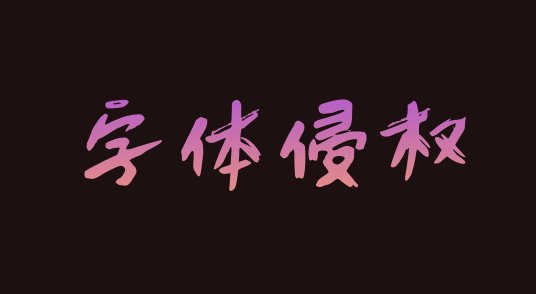
字体侵权案例1、关于字体侵权的案例,近期发生的。关注字体的应该都清楚,(电影《九层妖塔》字体侵权案有了最终的判决,7个字14万?)
据南都此前报道,向佳红起诉时称,电影《九层妖塔》中有七个字采用了其创作的字体,分别是鬼、族、史、华、夏、日、报。而《鬼族史》与《华夏日报》道具在影片中占有主导分量,是剧情的重要组成部分。“但我并未授权任何单位和个人使用‘向佳红书法字体’,更未允许任何单位和个人将字体用于商业营利和传播。”向佳红称,其在此套字体的属性中明确注明,该字体仅限于学习与交流使用,对个人用户免费,但商业用途须需经其本人授权。2013年12月,向佳红向广东省版权局申请作品名称为“向佳红毛笔行书字体”的作品著作权登记。
一审中,被告方辩称,涉案字体不是向佳红创作的,其对此不享有著作权;涉案单字仅出现在电影道具中,目的仅为说明道具名称,为汉字基本使用方法,在于传递其所承载的中文语言含义,而非主要展示其作为美术作品的艺术价值。此外,该使用方法使涉案单字具有了新的意义及功能,未影响其作为美术作品的正常使用,属合理使用。
一审法院经审理认为,向佳红主张权利的7个单字在断笔方式、布局结构、笔画粗细等方面均体现出了独特的美感。呈现出了不同于传统行书及其他常见字体的独创性表达,融入了书写者独特的智力判断和选择,属于我国著作权法中规定的美术作品。最后,四被告被判共同赔偿向佳红14万元。
一审判决后,梦想者电影(北京)有限公司、中国电影股份有限公司继续提起上诉,认为《九层妖塔》中对向佳红主张权利的7个单字的使用未违背其创造意图,其使用属于对涉案做转化性使用。同时,电影中对涉案作品使用仅作为道具的组成部分,在影片中短暂出现,如果署名会破坏电影画面的完整性。
二审法院经审理认为,电影拍摄过程中对涉案7个单字的使用属于复制行为,该行为未得到权利人的许可,即侵犯了著作权中的复制权,也不属于合理使用。最终,驳回上诉,维持原判。
字体侵权案例2、方正起诉暴雪公司的《魔兽世界》字体侵权并索赔1亿元,2009年追加索赔金额至4.08亿元。 2012 年 5 月法院做出终审判决,判定暴雪等被告方赔偿 200 万元。虽然赔偿金额大幅缩水,但依然远远超出授权费水平。
字体侵权案例3、热门影片《失恋33天》,因片头字幕等使用了未授权字体,最终赔付版权方2万元;